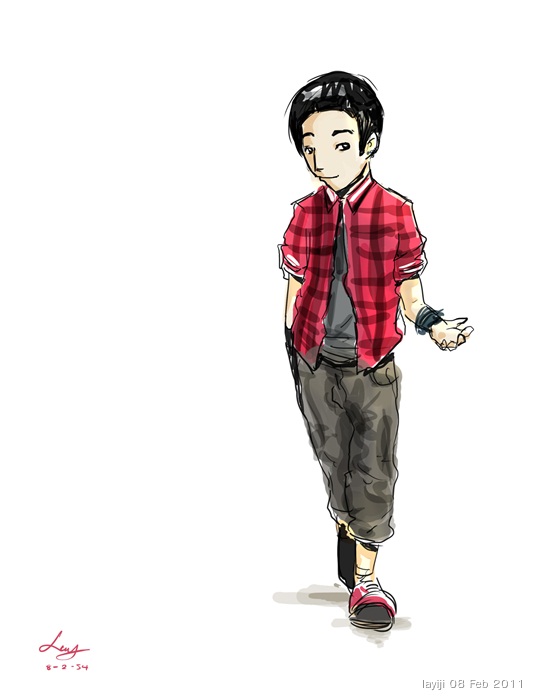
เลย์โชว์
นุ่มนวลชวนฝันมาก  :53:
:25:  หัวกลมก็หัวกลมเถอะ
วัยรุ่นไทยในปัจจุบัน
เย้ คิงออฟติ๊ด  \:07:/
ชุดสเก็ตช์สวยจังค่ะ  :25:
ป๋า นี่กระโดดก้าวข้ามคำว่าเทพ ไปแล้วใช่ไหม
แบบนี้เขาต้องเรียก ซุปเปอร์ไซย่าร่างสี่  :07: